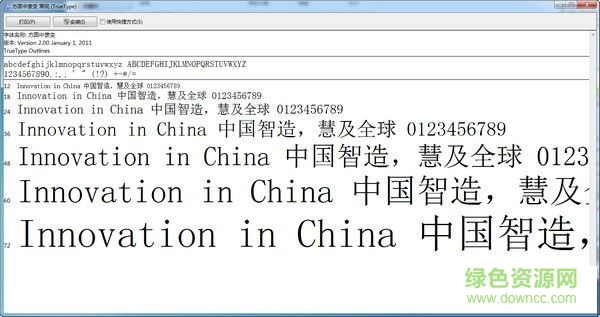
方圓中隸變體是由漢字演變而來的字體,特別適合廣告設(shè)計(jì)、海報(bào)設(shè)計(jì)等方便,有需要的朋友們歡迎下載!
徹底筆畫化。該字體適用于畫冊(cè)設(shè)計(jì),海報(bào)設(shè)計(jì)
圖書印刷等廣告設(shè)計(jì)場(chǎng)合使用
字型變圓形為方形,線條變弧線為直線,筆畫變繁雜為簡(jiǎn)省